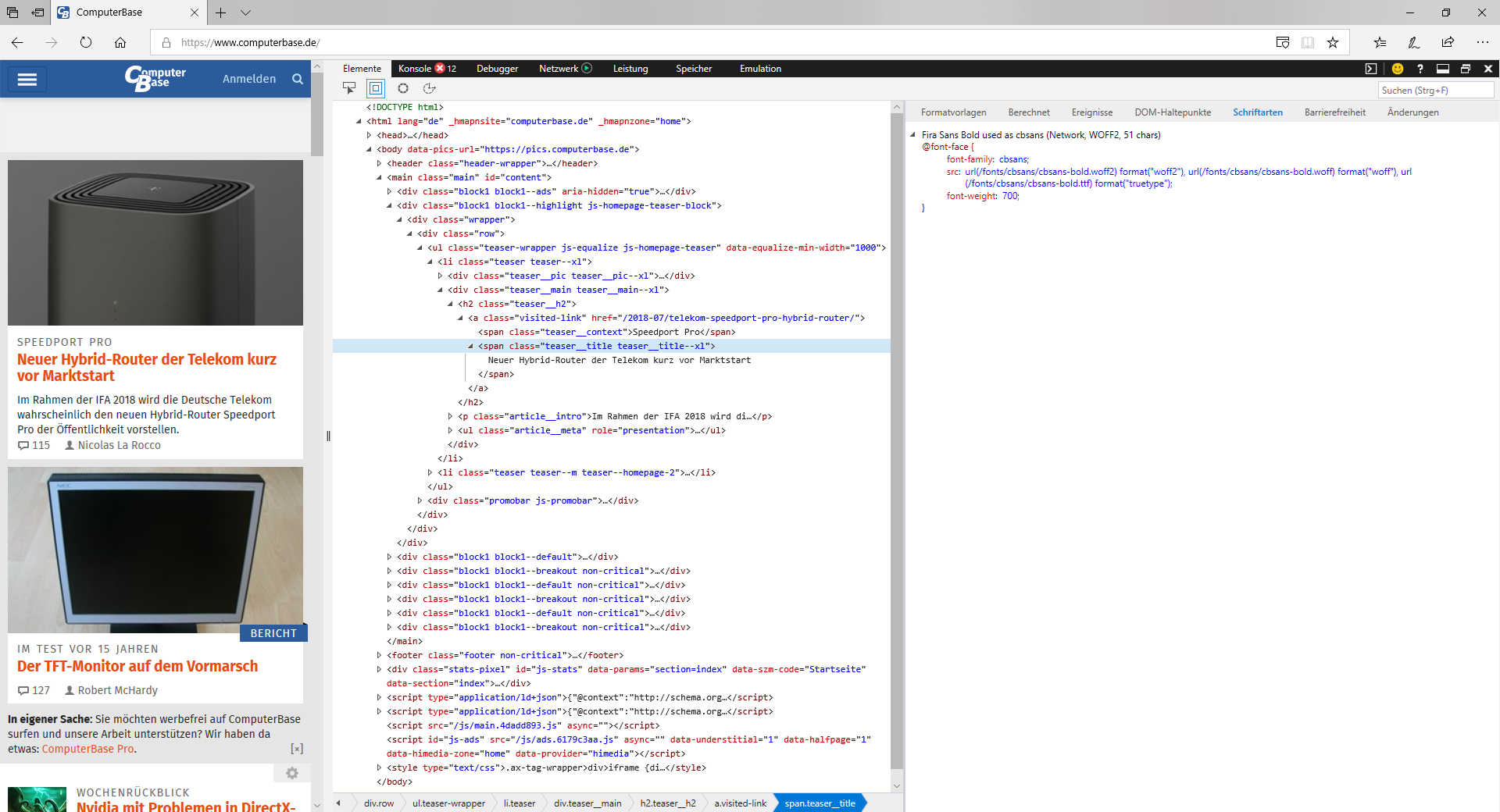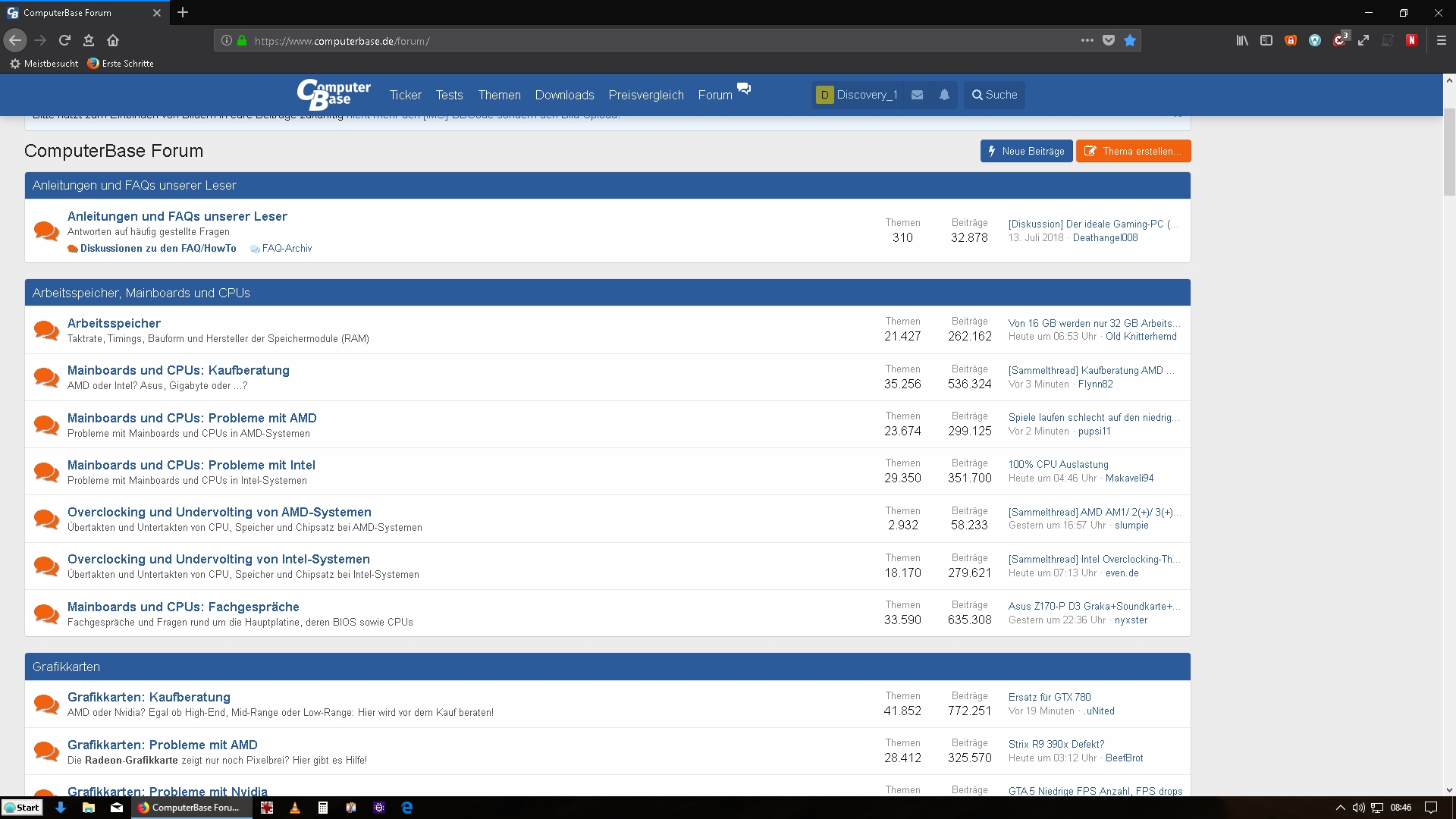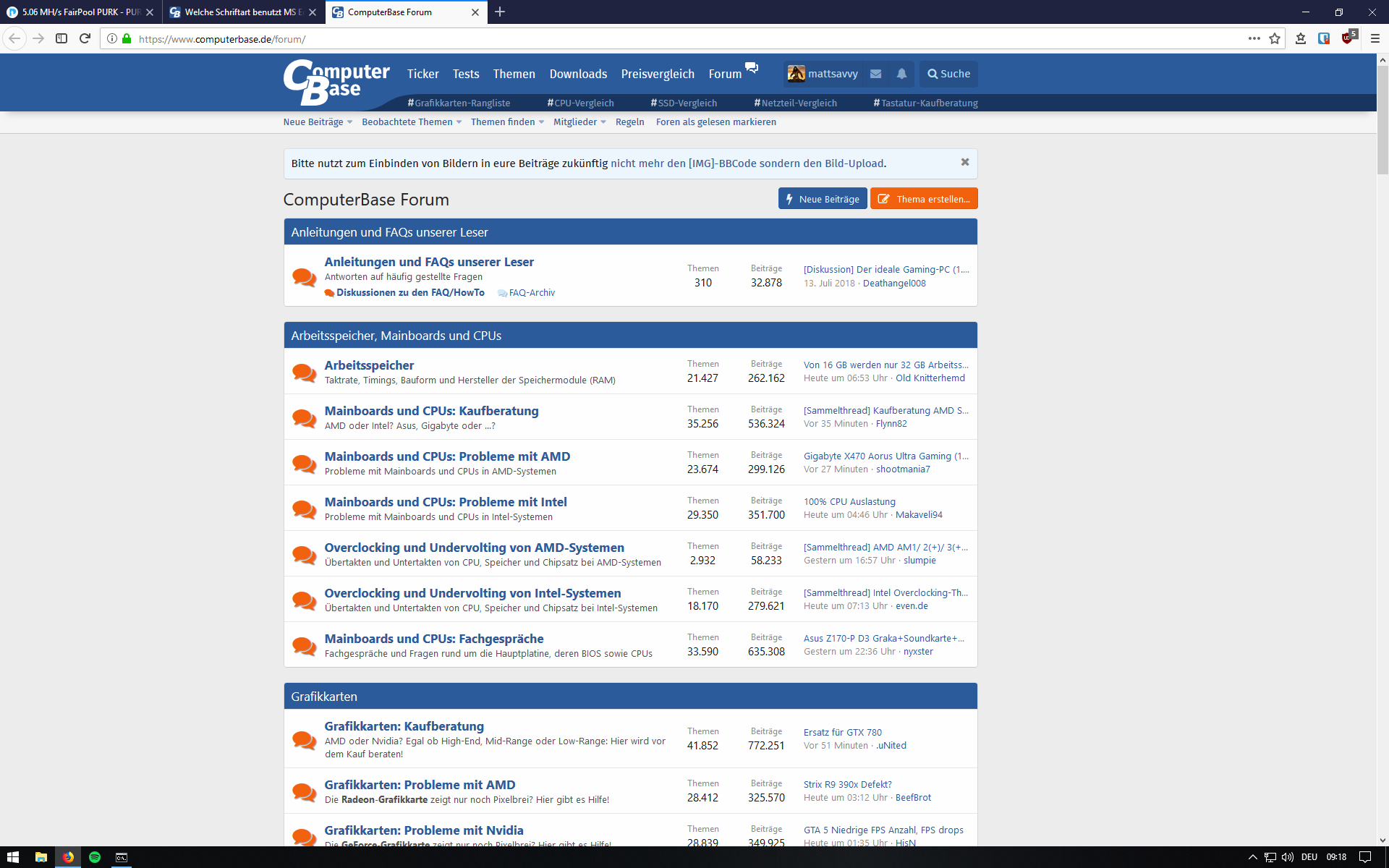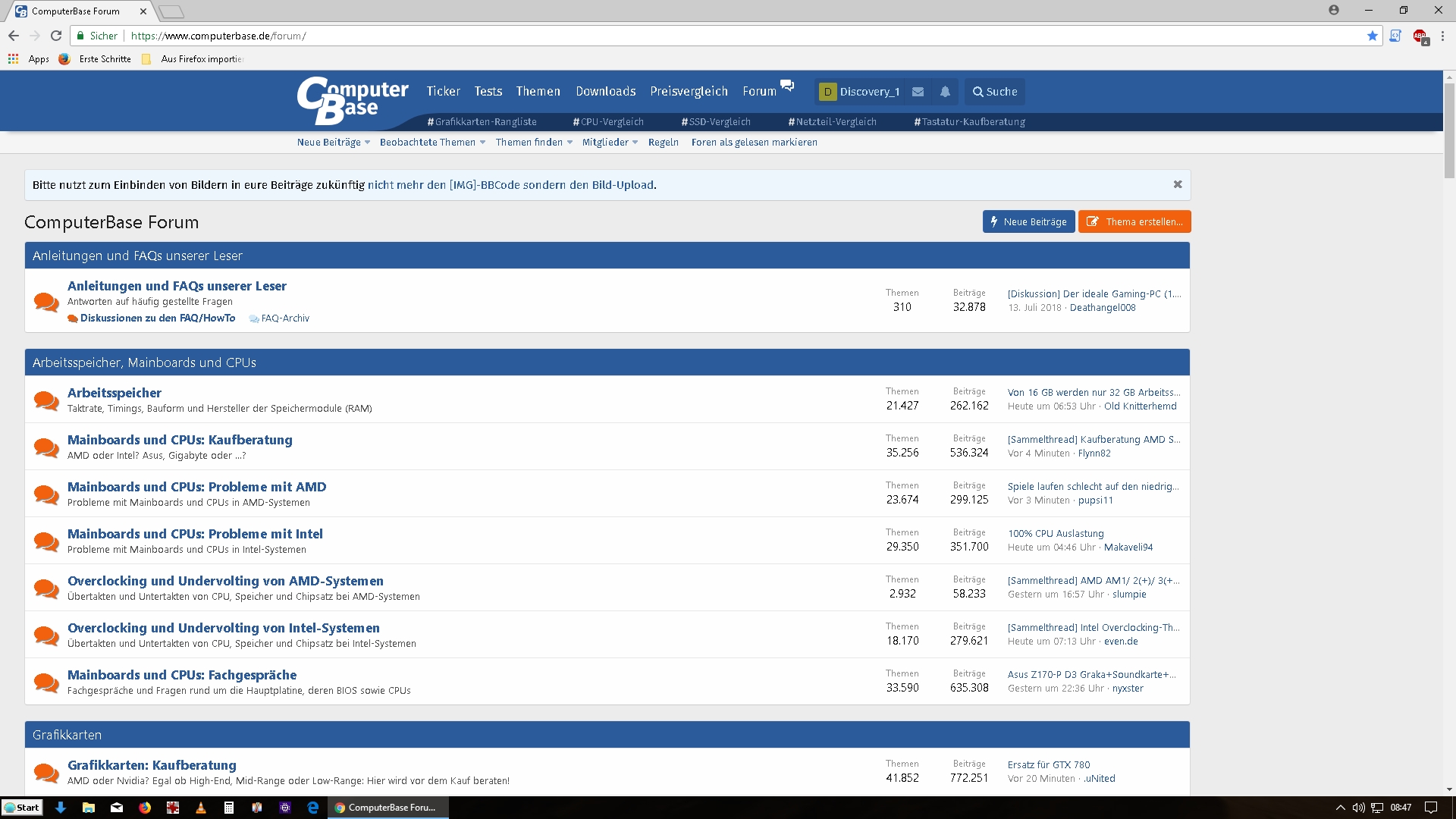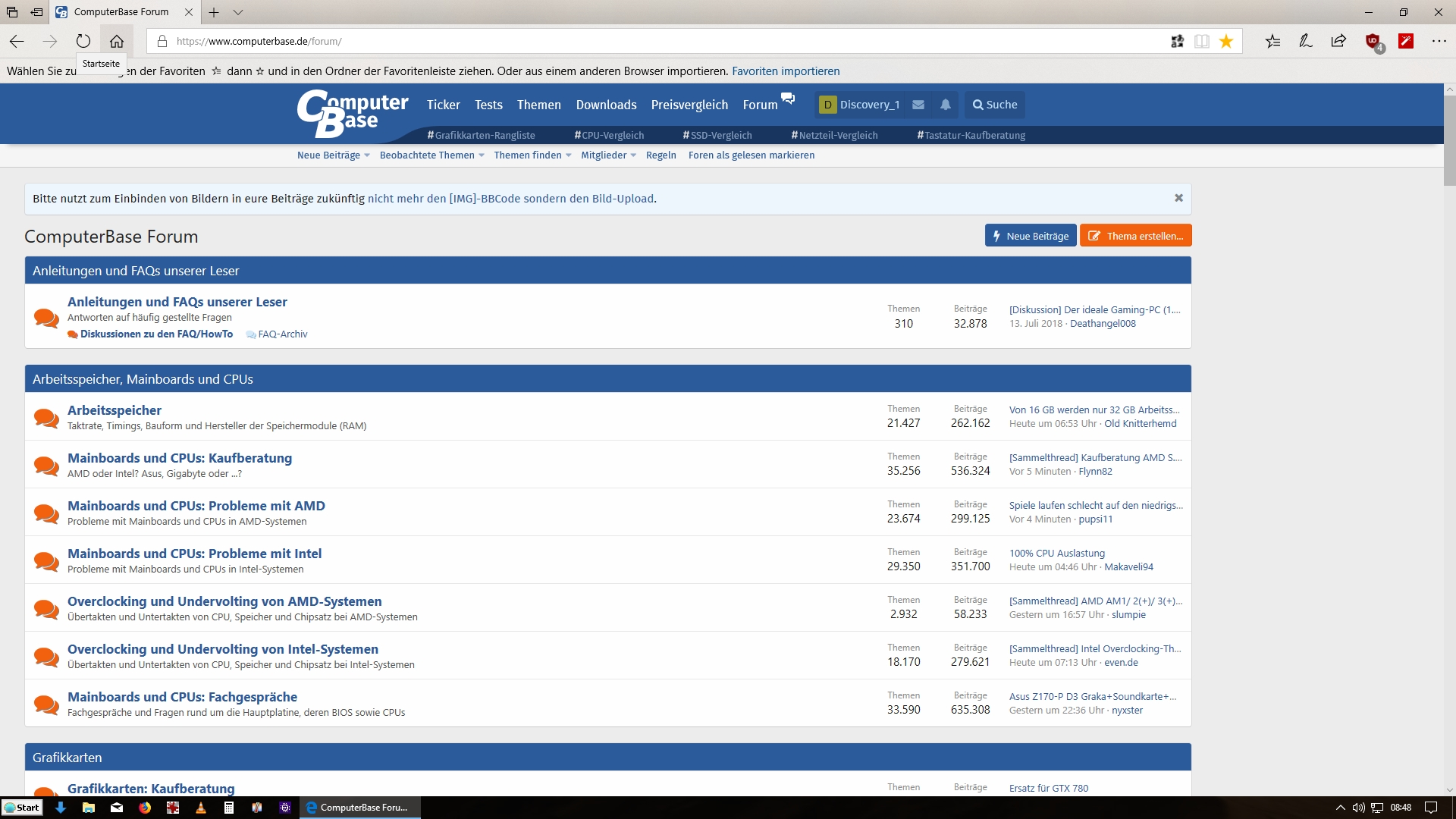
Welche Schriftart benutzt MS Edge?
Wie kann ich herrausfinden, welche Schriftart MS-Edge benutzt? Ich möchte das gern wissen, da die Webseiten-Darstellung von MS-Edge deutlich besser und damit angenehmer ist, als mit allen anderen Web-Browsern wie Firefox oder Chrome. Gerade hier bei CB wird die Webseite nur mit Edge angenehm dargestellt. Was spricht überhaupt gegen MS-Edge? Bin jahrelanger Firefox-User gewesen. Aber seitdem "Silverlight" nicht mehr unterstützt wird, kann man den Browser nur noch in die Tonne treten. Danke schon mal.
Du gehst einfach auf die Seite und machst auf irgendein Text Rechtsklick -> Element Untersuchen. Dann kommen die Dev Tools und dort musst du rechts auf den Reiter Schriftarten und dort steht die Schriftart. Im Fall von CB ist es "cbsans".
danke schon mal. Aber "cbsan" gibt es nirgends. Egal welsche Schriftart ich bei den anderen Browsern nehme, sieht die Darstellung von CB hinterher weiterhin bescheiden aus. Bei MS Edge ist aber es top!
Webseiten sehen eigentlich in jedem Browser ziemlich identisch aus. Ich sehe absolut keinen Unterschied zwischen CB in Edge, Firefox oder Opera. Sind in deinen anderen Browsern evtl. irgendwelche Einstellungen vorgenommen worden oder Plugins installiert die Inhalte blocken?
Nachtrag:
cbsans ist eine Webschriftart, sofern ein Browser die nicht nachladen kann, weil geblockt ist die nächste Variante Arial und ja die sieht nicht so toll aus.
Hier mal die Bilder: Auf den Bildern sieht man den Unterschied nicht so extrem wie in natura aber es ist doch schon ein großer Unterschied. Deaktivierte Ad-Blocker helfen in übrigen auch nicht.
Das ist jetzt mit den aktivierten Ad-Blockern. Aber mit deaktivierten sieht es exakt gleich aus.
Das liegt denke ich am Font-Smoothing.
Eigtl. müssten Chrome und Firefox das auch hinbekommen...
Das denke ich jetzt auch langsam. Immo habe ich auch keinerlei Probleme mit Edge. Ist halt ein bissl langsamer als die Anderen, das kann ich aber wohl verschmerzen.
So sieht die Seite bei mir in Firefox aus. Netflix und Prime laufen bei mir auch problemlos.
könnte vlt an einem nicht aktiviertem clear type liegen. müßte glaub ich irgendwo bei den bildschirmeinstellungen sein.
Ein ClearType Problem müsste aber eigentlich auch noch an vielen anderen Stellen auffallen.
Du meinst sicherlicher das Font Rendering von Edge und nicht die Schriftart. Das ist Geschmackssachen. Die wenigsten Leute finden den Ansatz von MS wirklich gut:
MS Edge hat hier wohl innerhalb von Windows eine Sonderstellung was das betrifft. Ich denke nicht, dass du das konfigurieren kannst.
Ich empfehle jedem das kostenlose MacType zu installieren, damit hat man in allen Windows Programmen, auch im Firefox, ein sehr viel besseres Schriftbild.